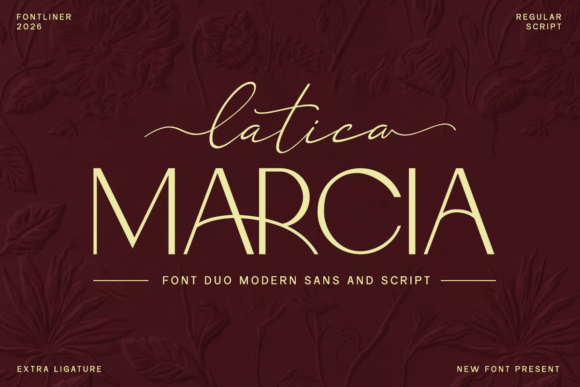
Latica Marcia
適切なデザイン要素を見つけるのは難しい場合がありますが、Latica Marciaは作品を即座に引き立てる優れたコレクションを提供します。
POD(オンデマンド印刷)製品、結婚式の招待状、またはソーシャルメディアのグラフィックを作成している場合でも、Latica Marciaは理想的です。